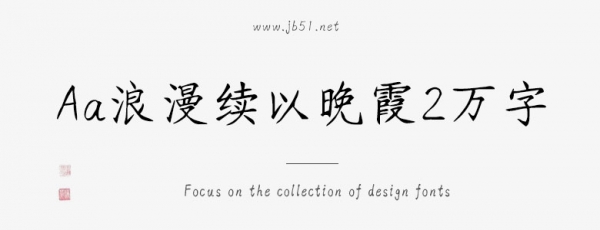
Aa浪漫續(xù)以晚霞2萬字是Aa字庫(kù)推出的藝術(shù)字體,字體筆觸略細(xì),字形端正,具有很好的視覺感,適合應(yīng)用于藝術(shù)設(shè)計(jì)、平面宣傳設(shè)計(jì)、網(wǎng)頁(yè)設(shè)計(jì),書法字帖等領(lǐng)域,歡迎需要的朋友下載使用。